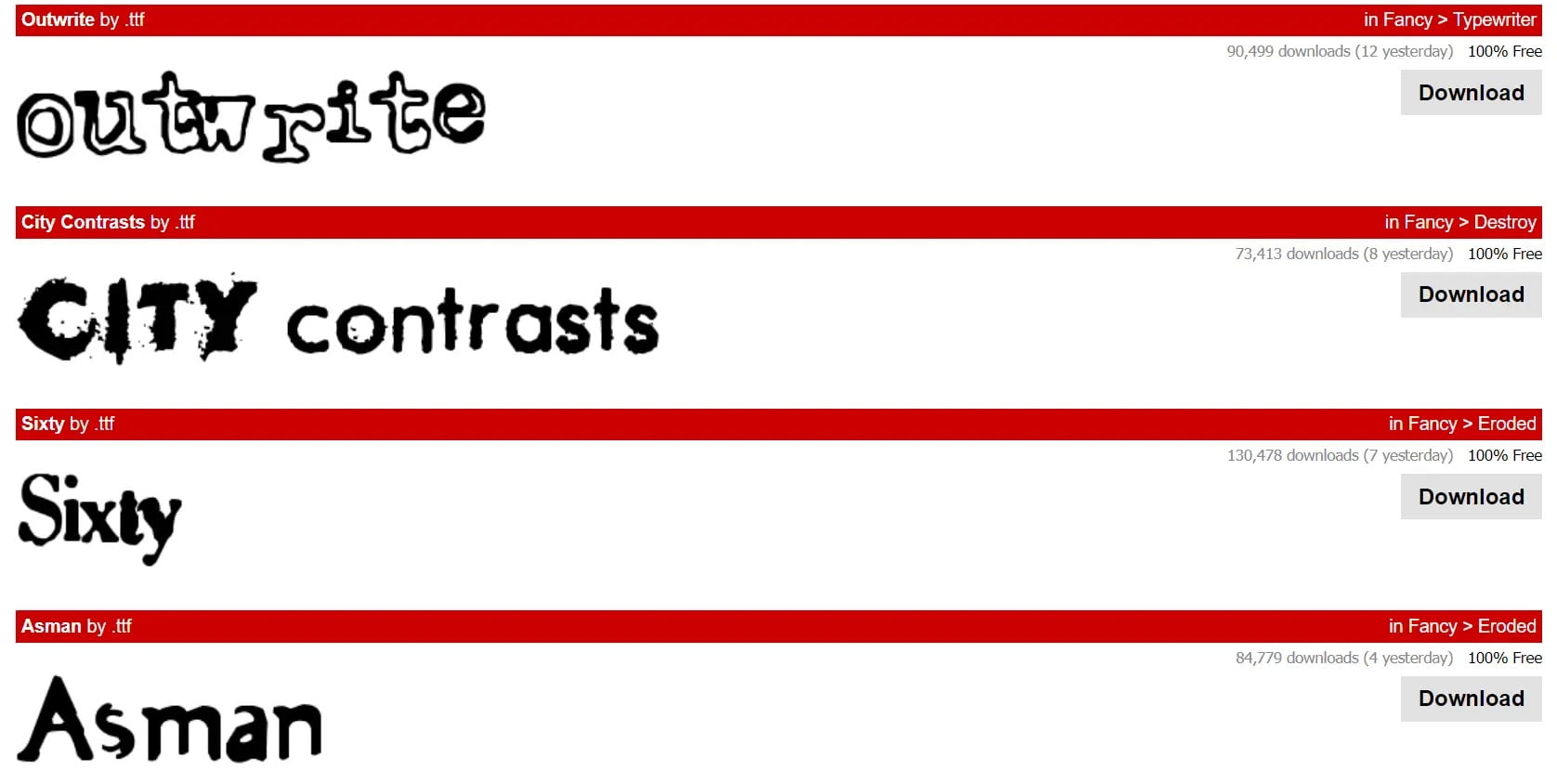
Download Font TTF – Font adalah salah satu penentu faktor agar sebuah gambar, video agar lebih menjadi aesthetic. Banyak sekali diluar sana font-font yang bisa kamu gunakan dan download untuk keperluan kamu.
Setiap font bahkan memiliki karakteristik dan fungsi yang berbeda-beda sehingga bisa kamu sesuaikan dengan kebutuhan.
Apa itu Font TTF?
Font TTF adalah sebuah tipe font yang tercipta sejak awal tahun 1980. TTF sendiri merupakan singkatan dari TrueType Fonts. Font ini berhasil tercipta berkat kerja sama antara Microsoft dan Apple.
Tujuan dari kerja sama ini adalah untuk membuat font dengan format yang sanggup terbaca oleh semua jenis printer di kala itu. Kerja sama ini terbukti berhasil dengan menciptakan font dengan format baru yang bisa kamu gunakan hingga sekarang.
Font dengan format baru ini bahkan membuat font dapat kita instal dengan lebih mudah, gratis dan pastinya bisa kamu gunakan secara lintas platform.
Font TTF sudah pasti berbeda dengan font OTF yang mana font OTF adalah jenis format font lainnya yang memiliki kemampuan untuk menambahkan ligatur dan juga karakter alternatif. Sehingga sangat berguna untuk kebutuhan desain grafis.
Misalnya saja jika ingin menggunakan huruf dengan desain dan bentuk lain maka jenis font OTF memiliki berbagai macam variasi yang lebih lengkap untuk kamu aplikasikan. Hal ini tentu saja berbeda dengan TTF yang hingga sekarang hanya bergantung pada tabel glyph.
Meski dari garis besar font OFT memiliki banyak kelebihan daripada font TTF. Tapi format font TTF masih menjadi favorit bagi banyak orang dan masih digunakan hingga sekarang di seluruh dunia.
Sebab tidak semua orang membutuhkan fitur yang ada pada font OTF. Sedangkan format TTF dianggap lebih mudah digunakan untuk segala keperluan. Misalnya jika kamu ingin membuat desain grafis maka font OTF lebih disarankan.
Namun jika hanya ingin mengerjakan tugas saja maka font TTF adalah pilihan terbaik yang bisa kamu gunakan.
Ada banyak sekali jenis dari font TTF yang bisa kamu gunakan dan pastinya bisa kamu sesuaikan dengan kebutuhan.
Font pertama yang kami rekomendasikan ada New Retro Style 3D by Hardik. Font ini memiliki gaya retro yang klasik namun dengan tampilan yang sederhana. Sangat pas jika kau gunakan sebagai font untuk bagian pembuka atau judul.
Berikutnya ada font yang bisa kamu gunakan untuk android. Yakni, Ariana Violeta by starinkbrush. Font ini memiliki tampilan yang khas dan sangat pas jika kamu gunakan sebagai font di android kamu.
Berikutnya ada Berlyna by Cempluk Studio yang merupakan salah satu jenis font gratis yang bisa kamu dapatkan. Font ini memiliki karakter yang unik dengan gaya font miring. Biasanya sangat cocok digunakan untuk font di android.
Download Font TTF Pixellab
Untuk kamu yang suka menggunakan aplikasi Pixellab untuk mengedit foto dan video. Maka font Chrusty Rock by cove703 ini bisa menjadi pilihan. Seperti yang kamu ketahui jika font TTF ini memiliki kelebihan.
Yakni fontnya dapat digunakan pada hampir semua platform. Baik sosial media hingga aplikasi edit foto dan video. Jika ingin memperindah editan foto dan video di aplikasi Pixellab. Maka kamu bisa gunakan font ini.
Download Font TTF Zip
Format font TTF ini memang bisa kamu unduh dengan format zip yang memudahkannya untuk kamu download dan akses. Sehingga kamu bisa menggunakan font untuk hampir semua keperluan.
Baik untuk membuat desain atau untuk membuat laporan bahkan juga bisa digunakan pada android.
Download Font TTF iPhone
Selanjutnya ada font Short Baby by starinkbrush yang bisa kamu gunakan untuk font iPhone. Kamu sudah tahu kan melalui penjelasan di atas jika font ini sendiri dibuat oleh iPhone dan Microsoft yang bekerja sama untuk membuat font yang kompatibel pada semua perangkat.